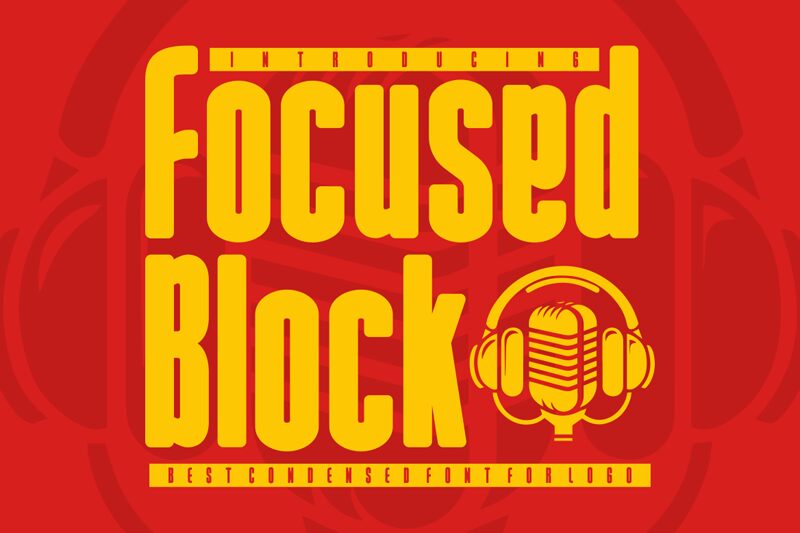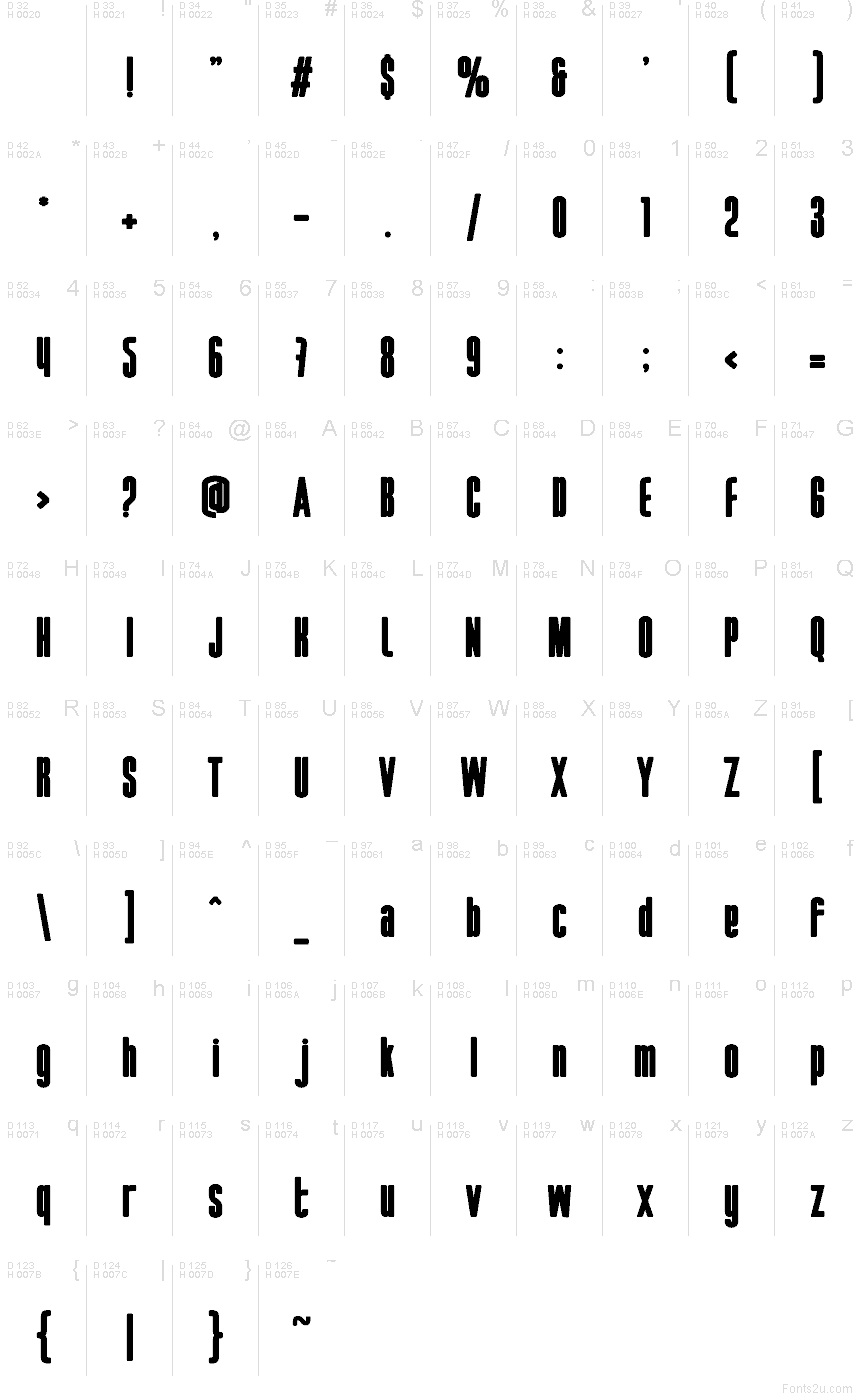
Focused Block Bold
Focused Block Bold od Shanaf Studio je bezplatné, zúžené bezpätkové písmo s výrazným, plagátovým vzhľadom. Písmená sú vysoké, masívne a tesne pri sebe, so zaoblenými rohmi a hlbokými zárezmi, čo dodáva abecede kompaktný rytmus – pôsobí športovo a zároveň industriálne.
Tento bezplatný font sa skvele hodí pre branding streetwearu, hudobné letáky, obaly, plagáty a titulky, kde krátke slová potrebujú maximálny dôraz. Dobre funguje aj pre monogramy a nápisy, pretože úzky, blokový štýl umožňuje písmenám do seba zapadnúť bez toho, aby stratili svoj výrazný tvar.